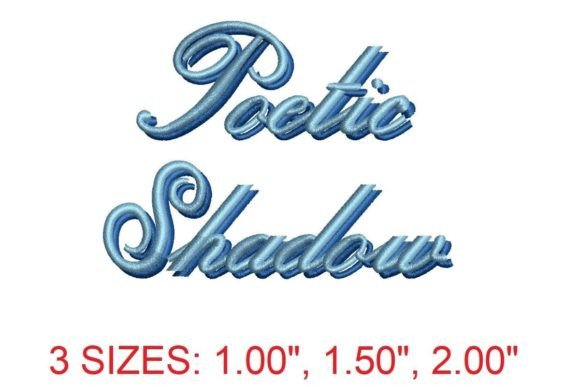
Poetic Shadow Embroidery Font
Việc tìm kiếm các thành phần thiết kế phù hợp có thể là một thách thức, nhưng Poetic Shadow Embroidery Font cung cấp một bộ sưu tập đặc biệt giúp nâng tầm công việc của bạn ngay lập tức.
Cho dù bạn đang tạo sản phẩm POD (In theo yêu cầu), thiệp mời đám cưới hay đồ họa mạng xã hội, Poetic Shadow Embroidery Font đều là một sự lựa chọn lý tưởng.